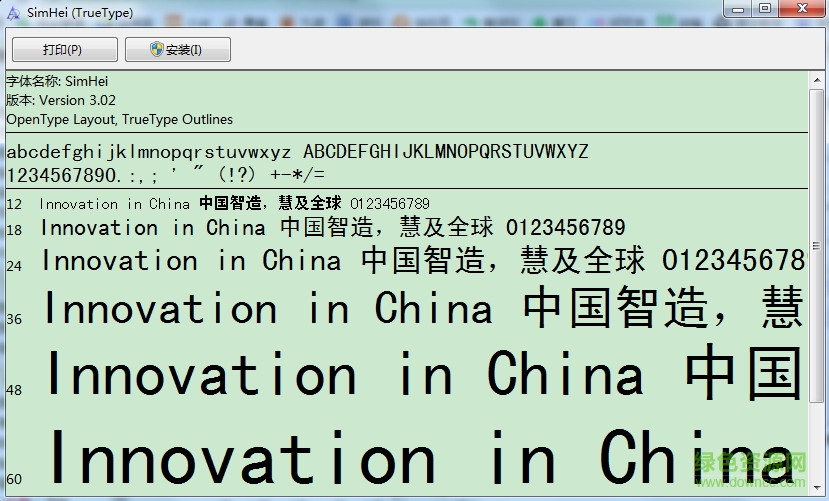
中易黑體是一款非常漂亮的黑體字體,這款字體字形大方,整體效果非常出色,可以廣泛應(yīng)用于廣告設(shè)計(jì)、宣傳海報(bào)、ppt等領(lǐng)域,喜歡的朋友歡迎來(lái)綠色資源網(wǎng)下載使用。
中易黑體字形非常有勁,流暢,字體工整??梢杂糜谂虐嬗∷⒌确矫?,用途廣泛。歡迎字體愛(ài)好者們來(lái)綠色資源網(wǎng)下載體驗(yàn)。